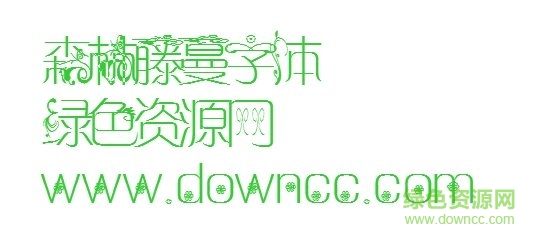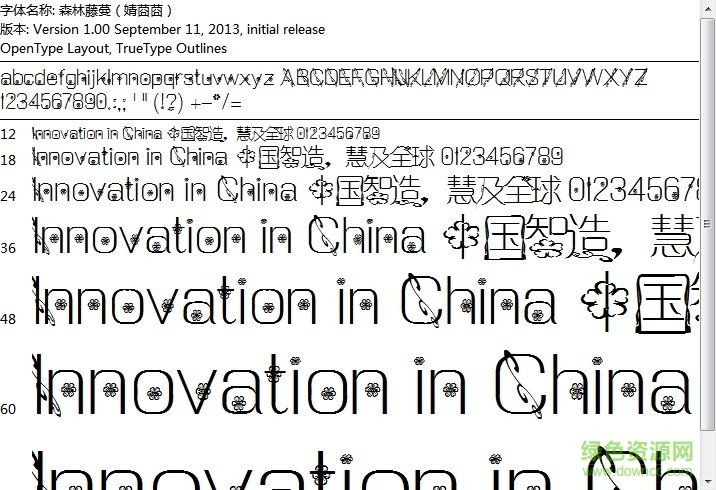
藤蔓字體是一款采用了花朵和樹枝點綴的藤蔓纏繞字體,給人春氣盎然的視覺體驗,感受置身于大自然中的純凈和美好,無需ps軟件,你就可以擁有這款藝術(shù)字體,安裝在手機(jī)上也很不錯哦,快來綠色資源網(wǎng)試試吧!
修改者給他起名為森林藤蔓字體,這款手機(jī)字體是將中倩體字體部分筆畫替換成了漂亮的花紋圖案。中倩體筆劃粗細(xì)對比適中,婉轉(zhuǎn)嫵媚,溫順乖巧,看似平淡無奇,卻能給人以美的感受。 插入花紋后增加了趣味性!